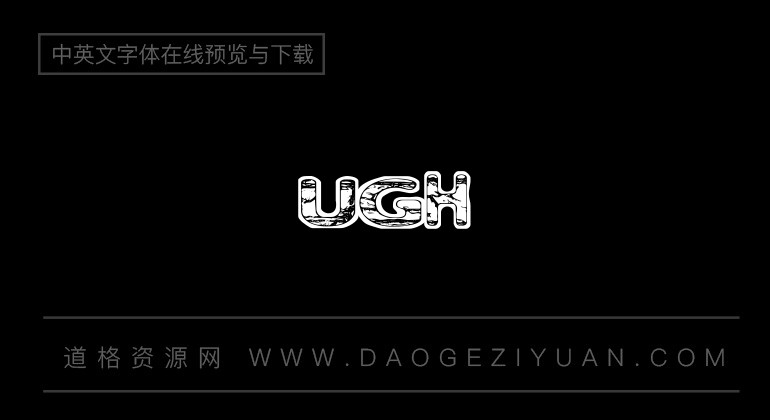
Ugh 字体是一款由设计师 Nina Stössinger 设计的无衬线字体。它于2015年发布,是一种非常独特的字体,它的字形充满了抽象的元素和几何形状。Ugh 字体拥有完整的拉丁字母、数字和标点符号,包括一些特殊字符和符号。它的设计灵感来自于手写的手稿,但同时也融合了现代设计的风格,使得它可以在不同场合下使用,例如印刷品、标志、广告和数字界面等。Ugh 字体的字母形状充满了轻快感和现代感,使得它成为一种非常有创意和独特的字体,可以吸引人们的注意力。内容介绍
Ugh是一款非常不错的手写艺术字体,具有很好的视觉感,适合于文化类的宣传设计、商业类品牌的广告和产品包装设计以及个性化文字排版等较多场景。